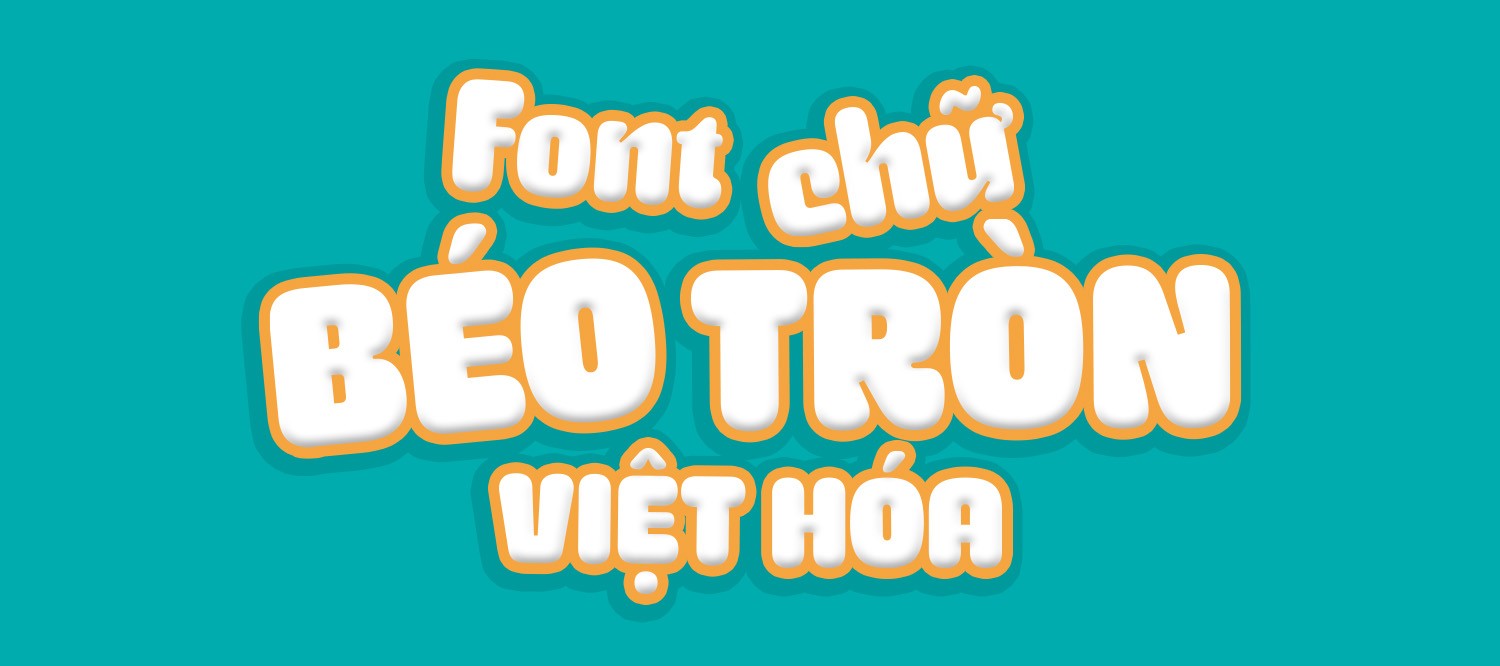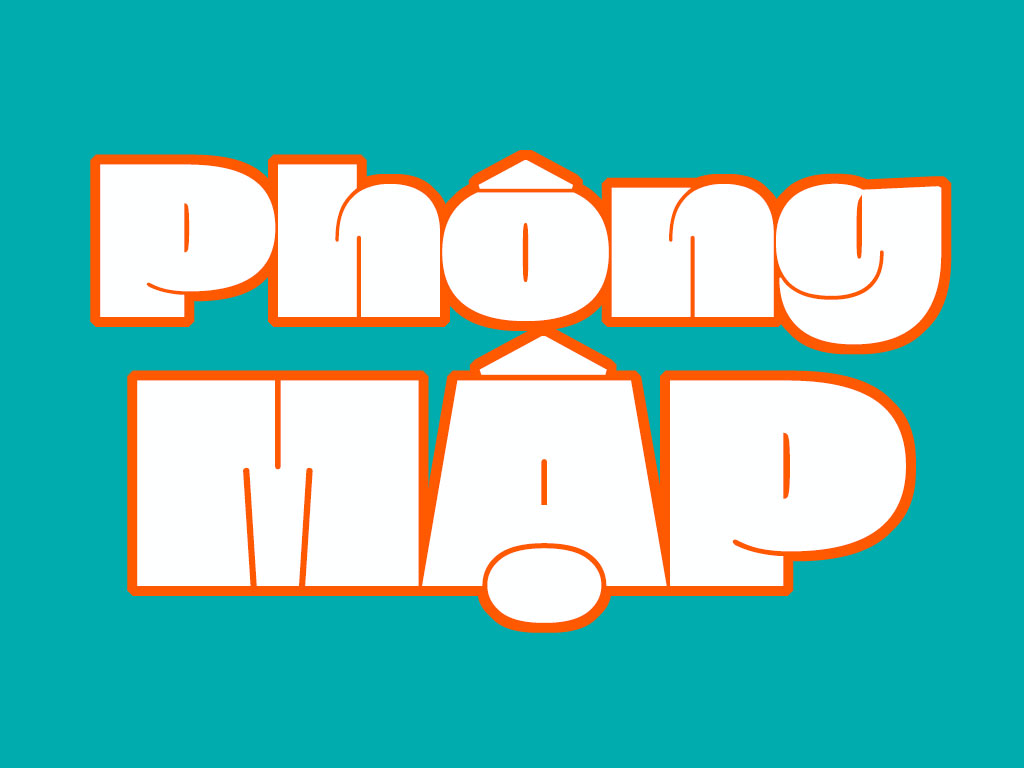
Khi thiết kế poster, banner hoặc logo thương hiệu, việc lựa chọn font chữ phù hợp có thể tạo ra sự khác biệt rất lớn cho tổng thể bố cục. Những font có nét chữ dày và rõ ràng thường giúp tiêu đề nổi bật hơn, đặc biệt trong các thiết kế quảng cáo hoặc nội dung truyền thông.
Vì vậy, nhiều designer thường tìm download font chữ béo để sử dụng cho các dự án cần tạo điểm nhấn mạnh mẽ. Tuy nhiên, không phải bộ font nào trên internet cũng hỗ trợ tiếng Việt đầy đủ. Trong bài viết này, Xưởng In Viva tổng hợp bộ download font chữ béo dễ sử dụng, hỗ trợ tiếng Việt và phù hợp cho cả thiết kế lẫn in ấn.
Font chữ béo là gì và vì sao được dùng nhiều trong thiết kế?
Font chữ béo là nhóm font có nét chữ dày, trọng lượng lớn và thường được thiết kế để thu hút sự chú ý của người xem. So với các font chữ mảnh hoặc trung bình, font chữ béo có khả năng tạo điểm nhấn thị giác mạnh hơn, đặc biệt khi sử dụng cho tiêu đề.
Trong thiết kế đồ họa, những font này thường được dùng cho headline, poster hoặc banner quảng cáo. Khi người xem chỉ có vài giây để nhìn vào thiết kế, một dòng chữ rõ ràng và nổi bật sẽ giúp thông điệp truyền tải nhanh hơn.
Đó là lý do nhiều designer thường tìm download font chữ béo để sử dụng trong các dự án thiết kế truyền thông, quảng cáo hoặc branding.
Tổng hợp bộ download font chữ béo nổi bật, dễ ứng dụng
Trước khi lựa chọn font cho thiết kế, bạn nên tìm hiểu một số bộ font phổ biến để đảm bảo chúng phù hợp với phong cách thiết kế của mình. Những font chữ béo thường có nét chữ dày, hình dạng rõ ràng và khả năng tạo điểm nhấn mạnh trong bố cục.
Dưới đây là một số gợi ý khi download font chữ béo được nhiều designer sử dụng:
Font Phong cách Ứng dụng Hỗ trợ tiếng Việt
iCiel Cubano Display Poster, logo
Gotham Bold Sans-serif Branding
Bebas Neue Condensed Banner quảng cáo
Anton Bold Tiêu đề lớn
Khi tải font chữ béo, bạn nên chọn những font đã được việt hóa hoặc hỗ trợ Unicode để tránh lỗi dấu tiếng Việt khi thiết kế.
05 đặc điểm nổi bật của font chữ béo trong thiết kế hiện đại
Font chữ béo không chỉ nổi bật về hình thức mà còn mang lại nhiều lợi ích trong bố cục thiết kế. Dưới đây là một số đặc điểm giúp loại font này được sử dụng phổ biến.
• Nét chữ dày và rõ ràng: giúp tiêu đề dễ đọc ngay cả khi nhìn từ xa.
• Tạo điểm nhấn mạnh: font béo giúp thu hút sự chú ý ngay lập tức.
• Phù hợp với thiết kế quảng cáo: poster, banner hoặc bảng hiệu đều cần font nổi bật.
• Dễ sử dụng cho branding: nhiều thương hiệu chọn font béo để làm logo.
• Phù hợp phong cách trẻ trung: font béo thường xuất hiện trong thiết kế năng động.
Nhờ những ưu điểm này, download font chữ béo trở thành lựa chọn quen thuộc của nhiều designer.
Ứng dụng thực tế của download font chữ béo trong thiết kế và in ấn
Khi được sử dụng đúng cách, font chữ béo có thể giúp thiết kế trở nên nổi bật và dễ ghi nhớ hơn. Loại font này thường được dùng cho các thành phần quan trọng trong bố cục như tiêu đề hoặc slogan.
Dưới đây là một số ứng dụng phổ biến khi tải font chữ béo cho thiết kế:
• Poster quảng cáo: font béo giúp thông điệp nổi bật.
• Logo thương hiệu: nét chữ dày giúp logo dễ nhận diện.
• Bảng hiệu cửa hàng: chữ rõ ràng giúp khách hàng dễ nhìn thấy.
• Menu nhà hàng: font béo giúp tiêu đề món ăn nổi bật.
• Bao bì sản phẩm: chữ dày tạo cảm giác mạnh mẽ và thu hút.
• Nội dung mạng xã hội: tiêu đề nổi bật giúp tăng khả năng thu hút.
Nhờ khả năng tạo điểm nhấn tốt, download font chữ béo thường được dùng trong các thiết kế cần truyền tải thông tin nhanh và rõ ràng.
Mẫu font chữ béo thiết kế poster sáng tạo
04 lỗi thường gặp khi tải font chữ béo về máy
Trong quá trình tìm download font chữ béo, nhiều người có thể gặp một số lỗi khiến font không sử dụng được như mong muốn.
• Font không hỗ trợ tiếng Việt: khi gõ tiếng Việt dễ bị lỗi dấu.
• File font bị lỗi: font tải về không thể cài đặt.
• Font quá dày: khiến bố cục thiết kế trở nên nặng nề.
• Không tương thích phần mềm: font hiển thị sai trong Illustrator hoặc Photoshop.
Mặc dù font chữ béo rất nổi bật, nhưng nếu sử dụng không đúng cách có thể khiến thiết kế mất cân đối. Vì vậy, designer nên lưu ý một số điểm sau.
• Không dùng cho đoạn văn dài: font béo phù hợp với tiêu đề hơn là nội dung dài.
• Kết hợp với font đơn giản: pairing với sans-serif mảnh giúp bố cục cân bằng.
• Điều chỉnh khoảng cách chữ: tracking hợp lý giúp chữ dễ đọc hơn.